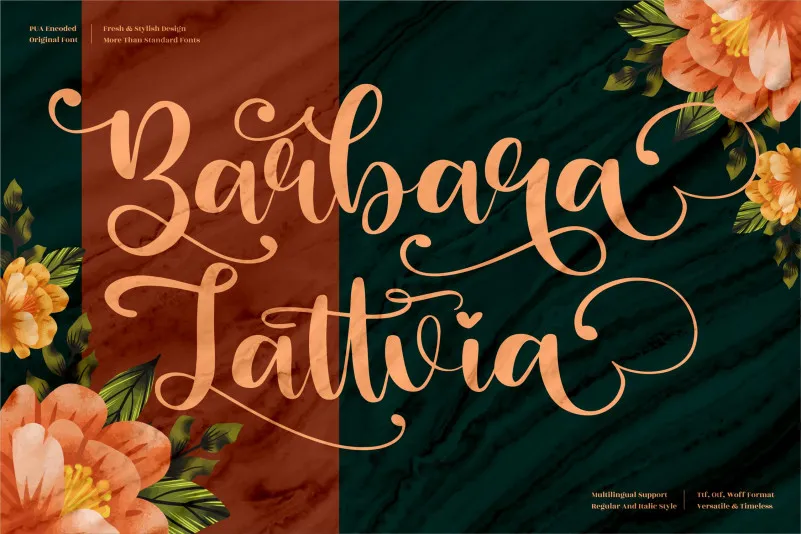
Barbara Lattvia Font
Este é um belo traço gótico romântico perfeito para diversos projetos, desde logotipos e embalagens até cartões de agradecimento e selos. Suavemente elegante e sofisticado, a Barbara Lattvia Font pode transformar qualquer projeto em uma experiência visual maravilhosa. É perfeito tanto para designs pessoais quanto para criações comerciais, fornecendo sempre um toque especial às suas idéias. Seja para o seu site de vendas online ou até mesmo para os selos que você usa na impressão em casa, essa fonte elegante será uma excelente escolha. Não importa qual projeto esteja fazendo, há algo neste traço romântico e delicado que certamente o deixará encantado.